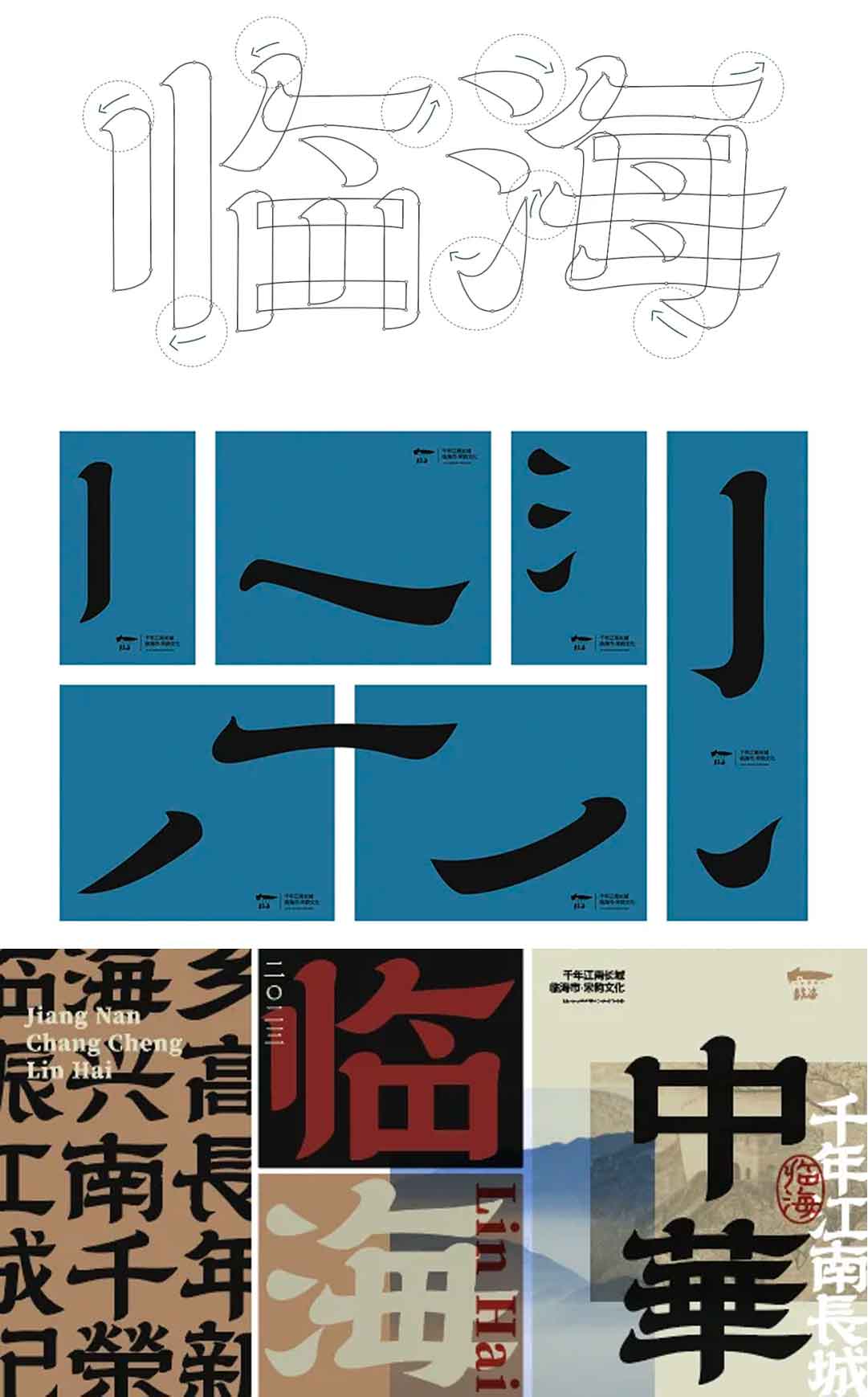
临海隶书
字体简介
创作背景:为打响 “千年台州府,江南真宋城” 文旅品牌形象,让文化传播更具辨识度,深度挖掘临海文化内涵,特推出这款具有临海独特风格和时代烙印的字体。
字体特点:结合了临海城市特质和隶书体,将千年古城、人文繁盛、山水之韵等展现得淋漓尽致。字体具有厚重、古典、拙朴的特质,旷达雄浑,古朴内敛。设计团队还创新地将山海元素融入字体笔画之中,增添了丝丝飘逸、自然之美。
版本信息:版本为 Version 1.00,发布于 2023 年 12 月 2 日,字重 1 个,收录简体和繁体汉字。